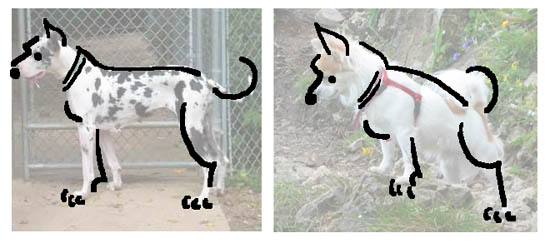
Wann ist ein Buchstabe ein Buchstabe....
ich habe da mal einen wahrscheinlich etwas merkwürdige Frage, die hier wie ich ich hoffe ganz gut aufgehoben ist.
Mich würde interessieren, ob es sowas wie "Richtlinen" gibt, die vorgeben wie bestimmte Buchstaben auszusehen haben.
Um es anders auszudrücken: Ab wann zb. ist ein "B" ein "B"?
wie weit darf die Entfremdung eines Buchstaben gehen, um noch als solcher anerkannt zu werden?
Um bei dem "B" zu bleiben, ist dieser Buchstabe solange als solcher gültig wie er zu entziffern ist? Oder gibt es in der Typographie eine gewisse Grenze die zb. sagt:"halt, dieser Buchstabe ist kaum noch als solcher zu erkennen und somit nicht mehr "gültig"".
es gibt meines Wissens keine verbindlichen Normen, wie weit ein Buchstabe verfremdet werden kann. Du hast dir aber eigentlich schon selbst geantwortet: Ein Buchstabe ist dann einer, wenn er gelesen werden kann. Kalligrafie und Grafitti spielen genau mit diesen Grenzen.
Die arabische Schrift ist da noch wilder, da kann eine Linie mit einem Schlusshaken und einem Punkt irgendwo schon ein Wort sein, was ich echt erstaunlich finde. Einfacher als eine Linie gehts nun wirklich nicht mehr.
In der chinesischen Kalligrafie geht's noch einen Schritt weiter: In der Konzeptschrift (caoshu) ist nicht die Lesbarkeit, sondern die (abstrakte) Ästhetik der Gestaltung das Hauptqualitätskriterium. Eine gute Kalligrafie nimmt darum Unlesbarkeit in Kauf.
Aber zurück zum Buchstabenthema: Ich denke, dass jeder Gestalter sich zu seinen Buchstaben stets neue Gedanken über die Annäherung an Grenzen machen muss. Wird's eine Leseschrift, muss sie so lesbar wie möglich sein, er wird sich also am überlieferten Formenkanon orientieren. Versucht er sich hingegen an einer Headlineschrift, kann er die Grenze zwischen Lesbarkeit und bloßer Form nach Belieben ausloten.
Außerdem kann ein und derselbe Buchstabe in unterschiedlichen "Sprachen" sehr verschieden ausfallen, man denke an die Unterschiede zwischen altdeutscher Schreibschrift, lateinischer Ausgangsschrift, französischer Schreibschrift usw.
Ein Buchstabe ist so lange ein Buchstabe wenn sein Grundgerüst (Graphem) bestehenbleibt.
Ob die Ausformung dann zweckmäßig ist (kommt auf den Zweck an) ist eine andere Frage.
Ist denn das Graphem sozusagen nur durch die Überlieferung definiert? Wann ist z.B. ein B nur unten offen oder ist es dann ein unten geschlosseneres R? Regelt das "unsere" Empfindung? Kann man sich beispielsweise ähnlich ambivalente "Buchstaben" vorstellen, die erst mit ihrer Verwendung in einem Wort (Kontext, Vokalbular) Eindeutigkeit erhalten?
5TOCK oder STOCK? BALL oder 8ALL? B1ER oder BIER? ZOO oder 2OO?
Interessantes Denkspiel ...
Die Bandbreite zwanglos lesbarer graphischer Konfigurationen eines Buchstabens ist doch phänomenal, und Eineindeutigkeit im mathematischen Sinne eher die Ausnahme.
Bei manchen verzierten Frakturversalien habe ich große Schwierigkeiten, sicher zu erklären, warum ich sie meist richtig lesen kann.
Das sollte ich einem kulturinteressierten Amerikaner nämlich auseinandersetzen, der unsere Fraktur faszinierend fand, aber vor den Versalien kapitulieren mußte.
Ich glaube es gibt eine Art "Grundschema" das den Buchstaben und damit der Buchstabenerkennung zugrunde liegt. Dieses Grunschema kann nach belieben manipuliert und verfremdet werden, muss im Kern jedoch noch erkennbar sein.
So könnte es z.B. ganz simple "Anleitungen" für einen Buchstaben geben, so wie man etwas Grundschulkindern ein "B" beibringt.
Allerdings scheint mir die Formulierung dieser Anleitungen nicht so einfach zu sein......
Wie soll man das in einer einzigen, möglichst simplen Regel formulieren, dass das:
immer ein und derselbe Buchstabe ist? Es muss da aber irgendeine Regel geben, sonst würde unsere Wahrnehmung ja nicht funktionieren ...
Da spielt unsere Wahrnehmung sicher eine ganz wichtige Rolle. Das Gehirn nimmt bevorzugt in Bildern wahr und gleicht auch Bilder gegeneinander ab; das ist ein komplexer Prozeß der Mustererkennung. Und es ist extrem schwer, dies rational zu erklären. Nur als Beispiel: In den meisten Fällen haben wir überhaupt keine Schwierigkeiten, aus 20 Photos mit 19 Hunden und einer Katze die Letzte mit einem Blick heraus zu fischen. Und das, obwohl die Hunde alle komplett unterschiedlich sein können, was Farbe, Größe, Rasse etc. angeht. Wir erkennen sofort, welches die Hunde sind (sofern man nicht sehr merkwürdige Exemplare mit einmischt).
Und jetzt umgedreht: Versucht doch mal, treffsicher einen Hund zu beschreiben. Wie genau beschreibt man den Unterschied zwischen einem Hund und einer Katze? Die Mustererkennung erledigt das Gehirn im Bruchteil eine Sekunde, die rationale Erklärung ist für viele, die ich selber getestet habe, fast unmöglich. Und das gilt für fast Alles im täglichen Leben; wir haben kein Problem, auf einem Bild einen Tisch als solchen zu benennen, es wird aber deutlich schwieriger, eine Definition eines Tisches zu finden, welches die Identifikation mit an Sicherheit grenzender Wahrscheinlichkeit erlaubt. Ein flüchtiger Blick hingegen ist dafür völlig ausreichend.
@Pachulke: :lol:
@Franz Müller: Der Chihuahua ist im Grunde nichts anderes als ein Sütterlin-h. Einmal als Hund identifiziert erkennt man ihn ab sofort immer wieder.
Wer übernimmt jetzt die Ehrenrettung des Sütterlin-hs? :twisted:
@Norbert: ist das nicht eher ein Spitz? Aber ansonsten trifft es die Sache wohl!